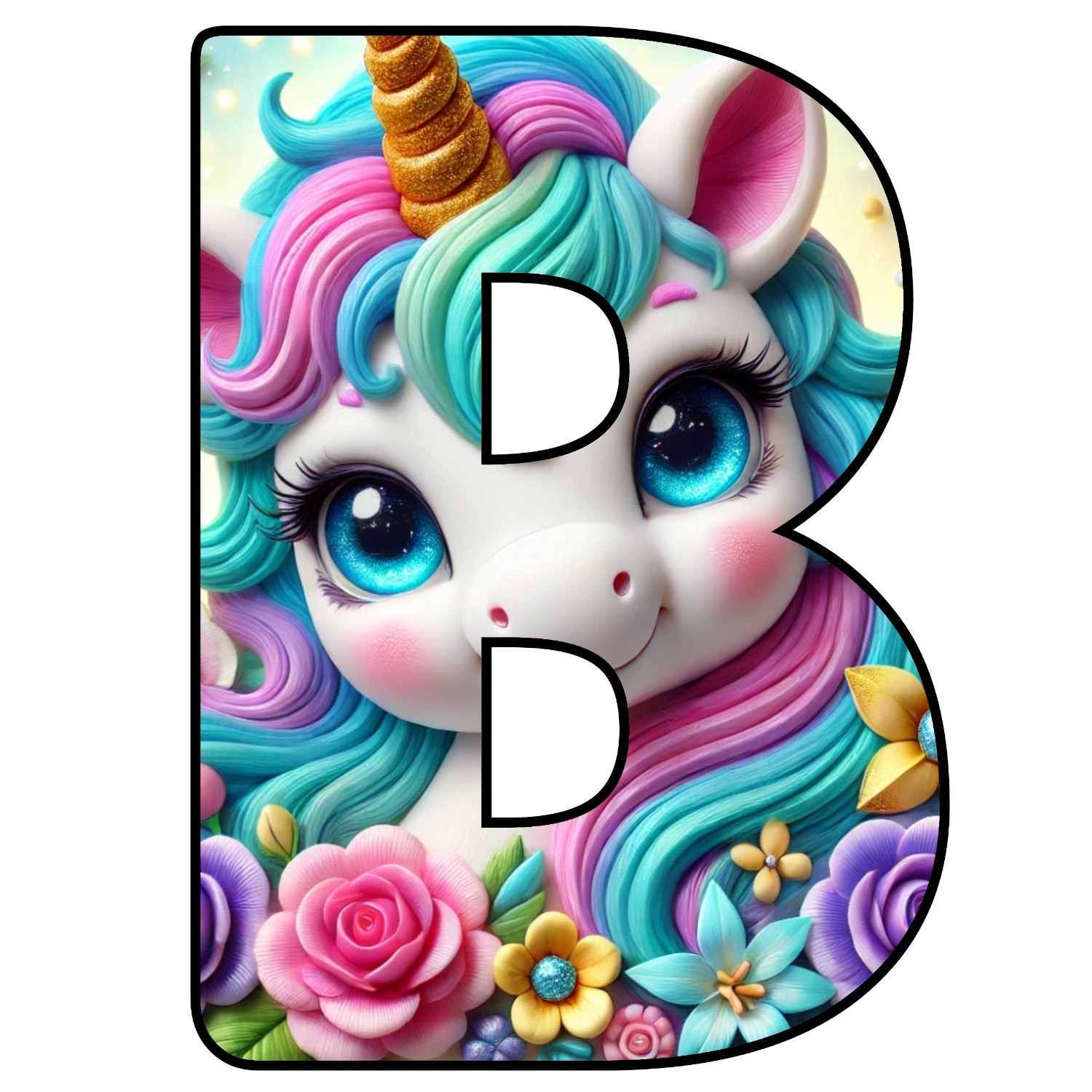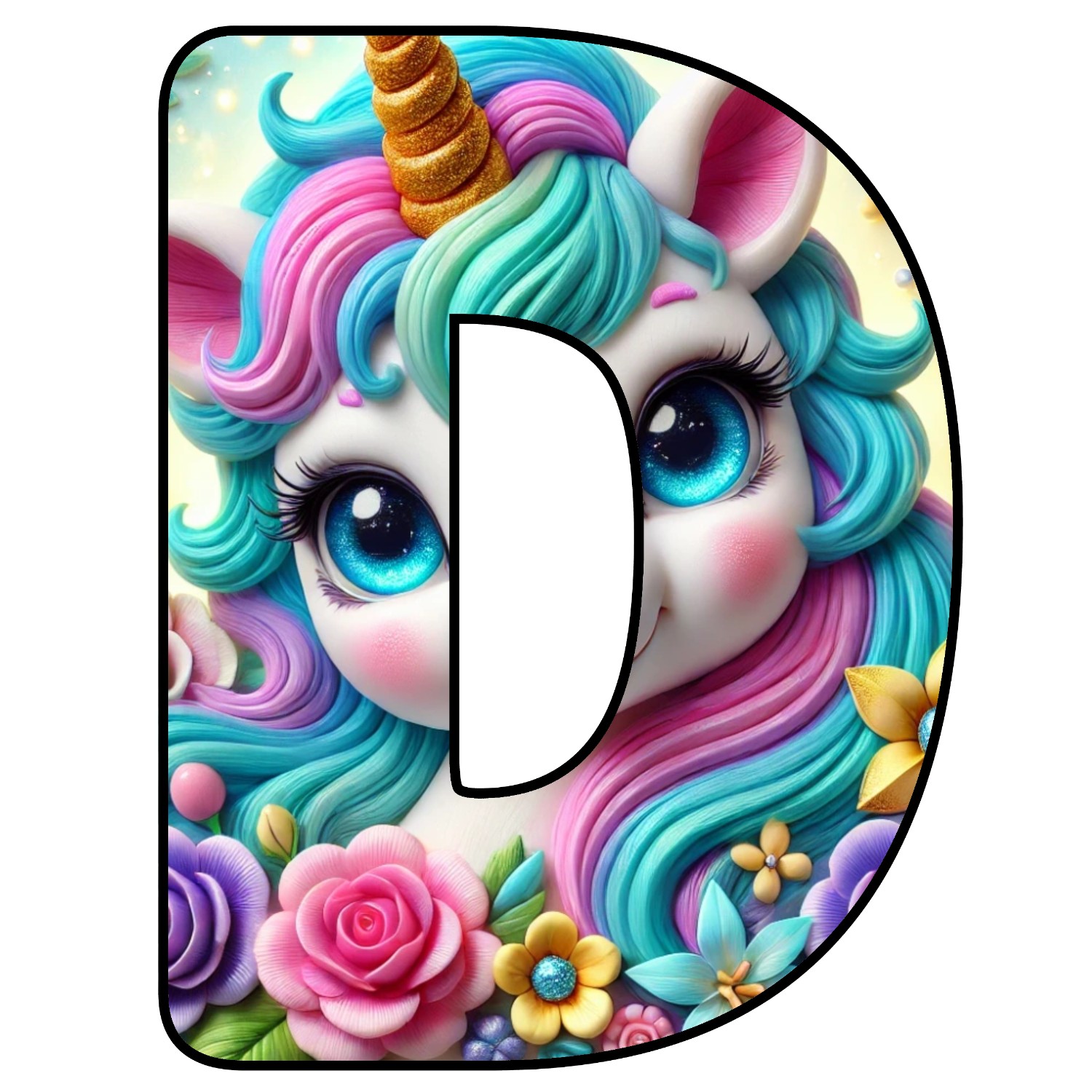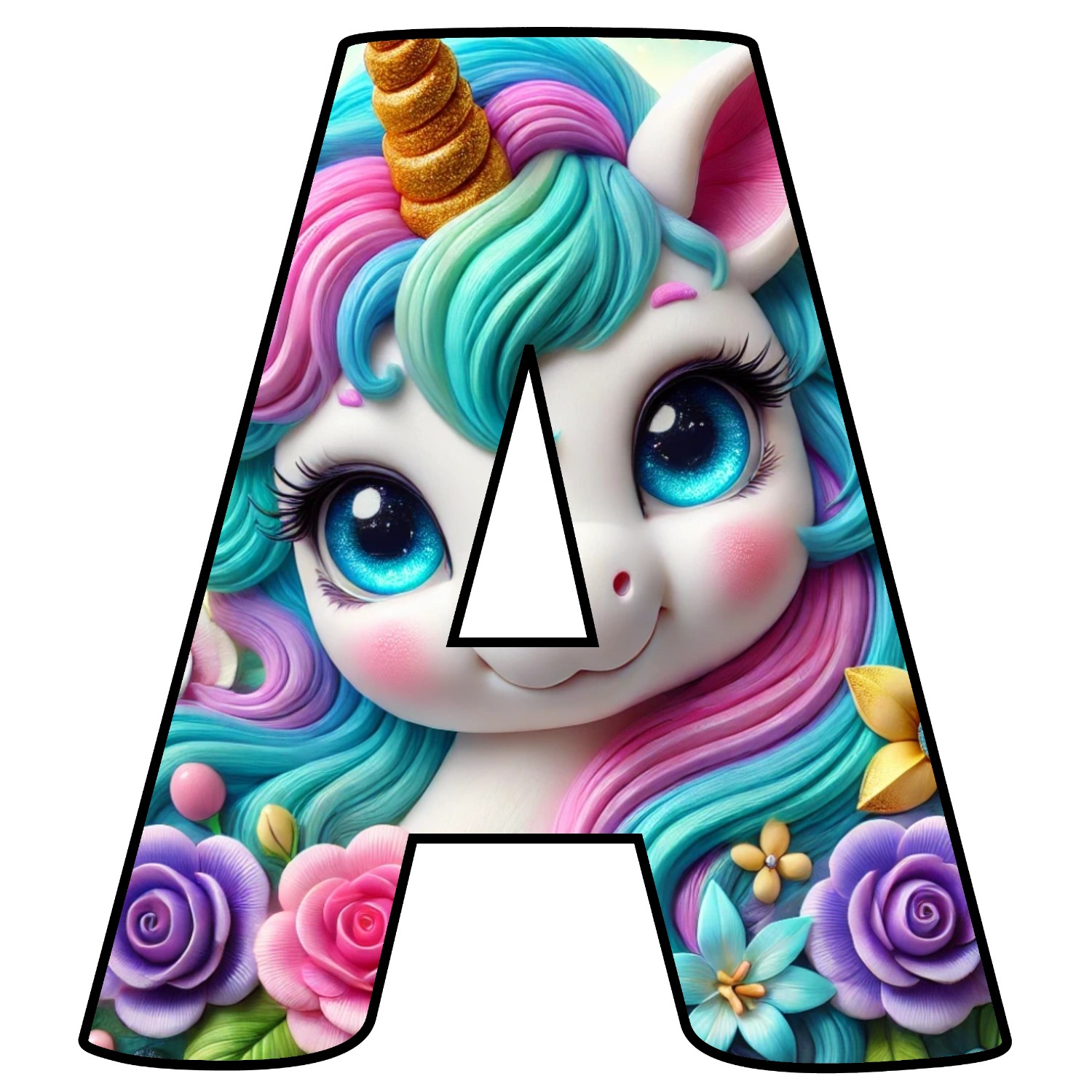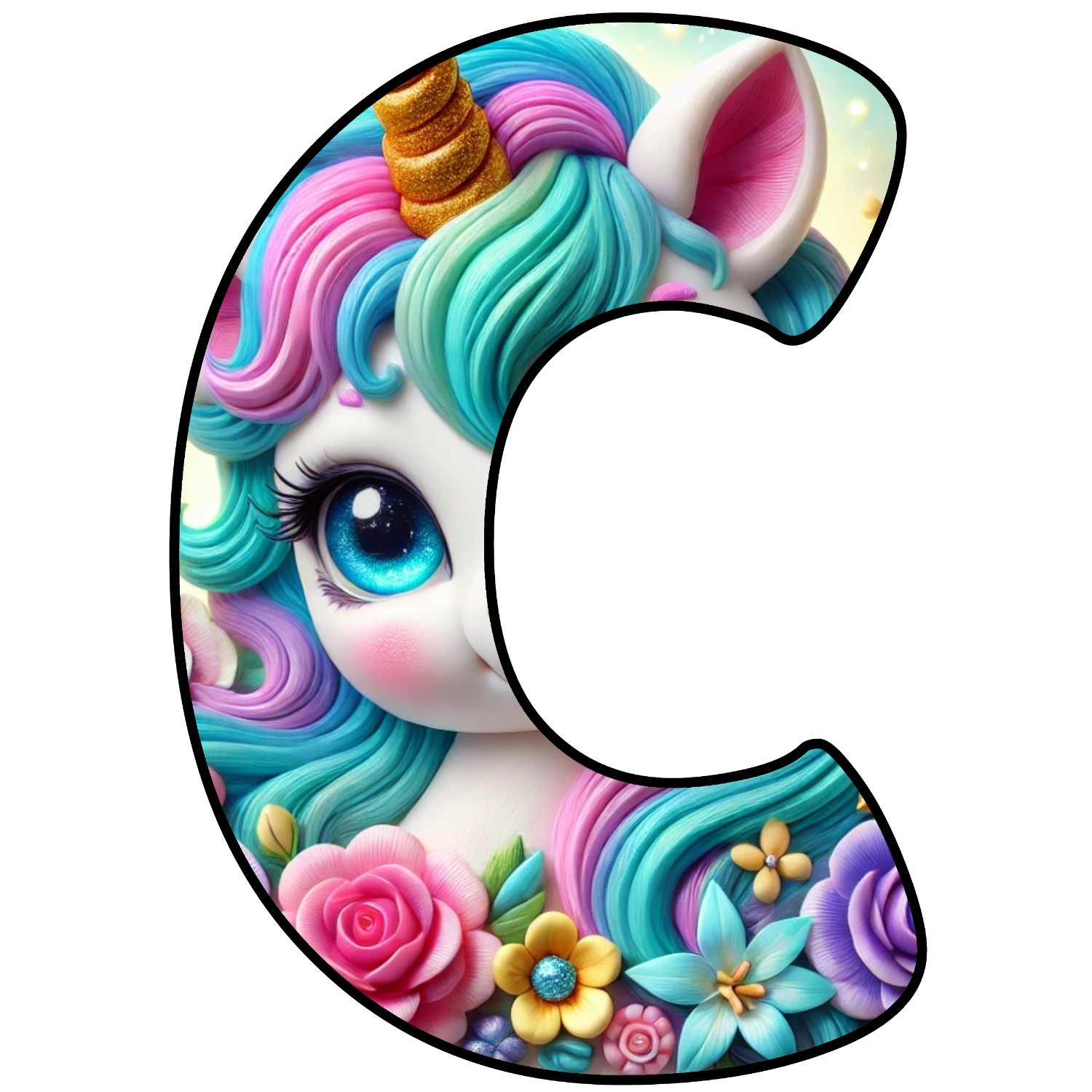
¿Te gusta este diseño de Alfabeto de Unicornio para imprimir? Con FontPic podés crear letras, números y plantillas personalizadas usando este mismo fondo o cualquier imagen que vos elijas. Subís tu foto, escogés el estilo y en segundos obtenés un alfabeto completo con el mismo diseño y coherencia visual.
🔍Este estilo es ideal para carteles de cumpleaños, aulas, decoración de fiestas y proyectos escolares. Las letras salen listas para imprimir, con alta calidad y proporción cuadrada, perfectas para recortar o montar en banners.